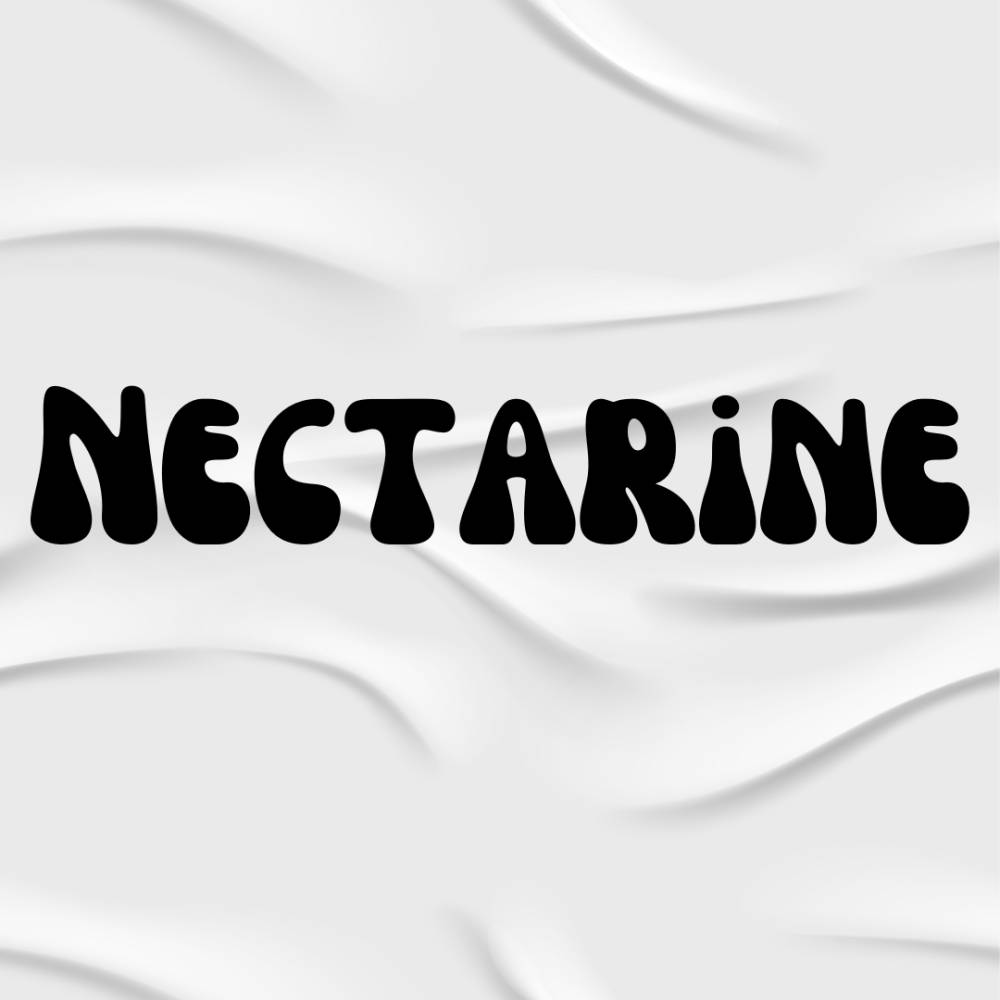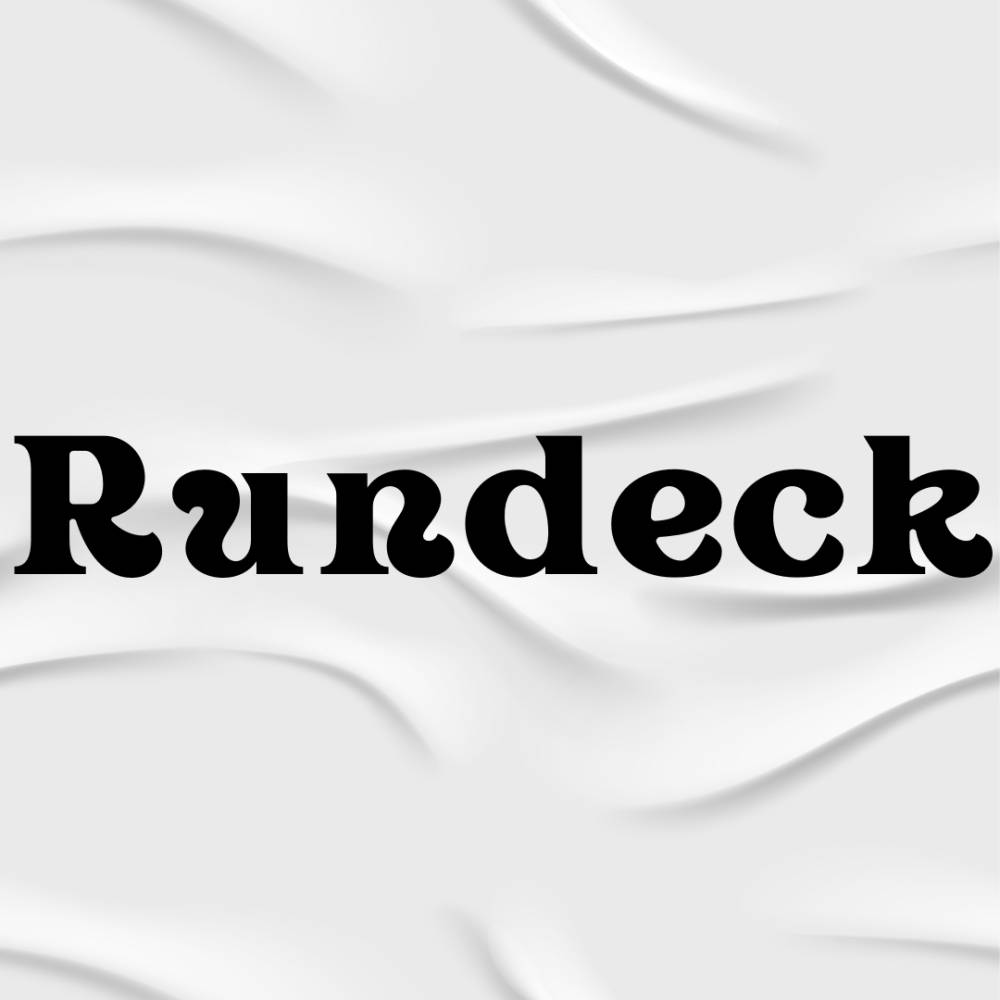
7 Rekomendasi Font Vintage Canva buat Desain Retro
Seiring dengan berkembangnya desain grafis, sentuhan retro kembali menjadi tren yang digemari. Desain-desain yang mengusung nuansa vintage mampu memberikan kesan klasik, unik, dan juga menghadirkan nostalgia. Namun, untuk benar-benar membuat desain yang memberikan pengalaman kembali ke masa lalu, adalah hal yang tricky.
Bukan hanya elemen gambar dan warna saja yang perlu diperhatikan, font menjadi elemen yang patut dipikirkan untuk menarik perhatian audiens. Untuk memudahkanmu membuat desain retro yang mampu membuat audiens bernostalgia, berikut adalah tujuh rekomendasi font vintage Canva gratis yang bisa kamu coba.
1. Bright Retro
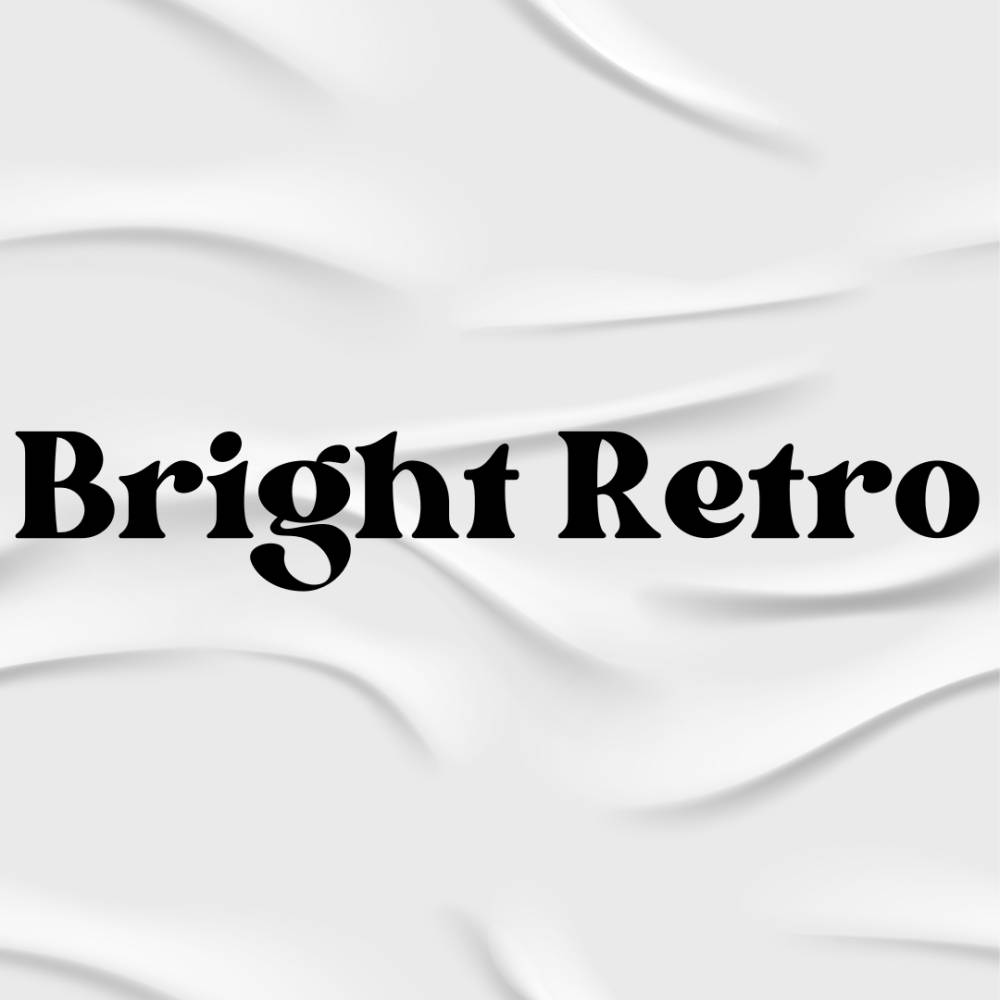
Ilustrasi font canva (dok. Canva) Font Bright Retro membawa mu kembali ke era 80-an dengan karakter tipografi yang bold dan dinamis. Dengan bentuk huruf yang mencolok, Bright Retro mampu menciptakan kesan yang ceria dan penuh semangat, sangat cocok untuk desain yang ingin menonjolkan nuansa retro yang cerah dan positif. Huruf-hurufnya yang berani memancarkan energi positif dan keberanian dalam setiap desainnya.
Kombinasi antara ketajaman sudut dan kejelasan huruf membuat Bright Retro menjadi pilihan yang menarik buat kamu yang ingin menyelami keindahan era 80-an dengan sentuhan modern. Dengan gaya tipografi yang khas, font ini tidak hanya menjadi penghias visual, tetapi juga alat untuk menggambarkan kegembiraan dan kebebasan dari zaman yang lebih simpel. Kesederhanaan dan keberanian Bright Retro membuatnya menjadi pilihan yang tak terelakkan bagi para desainer yang ingin menghadirkan suasana nostalgic dalam desain mereka.
2. Harlow
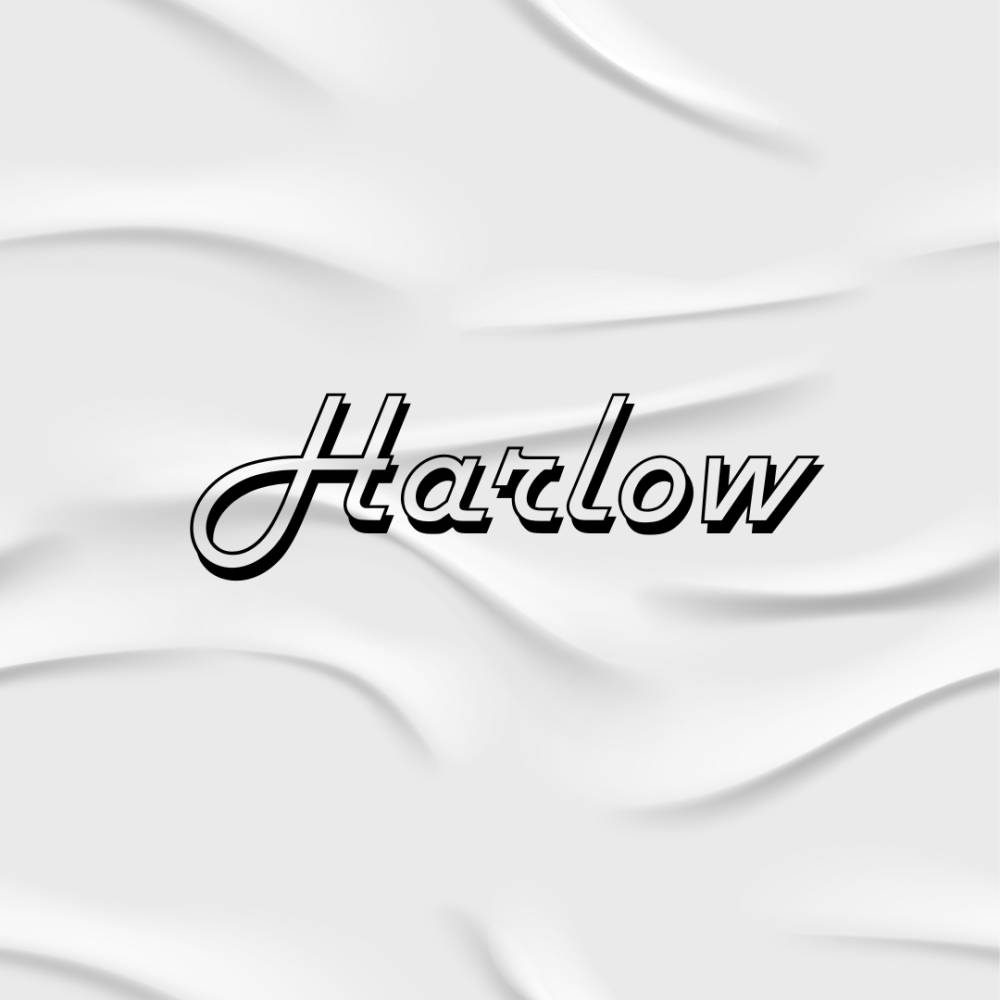
Ilustrasi font canva (dok. Canva) Font Harlow memukau dengan garis-garis elegan dan kesan klasik yang memperkaya setiap desain retro. Dengan huruf yang melengkung secara anggun, Harlow memberikan sentuhan glamour yang tak tertandingi pada setiap desainnya. Kelembutan dan keanggunan karakter hurufnya menjadikan Harlow sebagai pilihan ideal untuk desain yang mengusung gaya vintage yang lebih mewah dan anggun.
Kombinasi antara elemen-elemen artistik dan kejelasan tipografinya membuat Harlow cocok digunakan dalam berbagai konteks, dari desain poster hingga kemasan produk. Gaya yang timeless dari Harlow tidak hanya menciptakan estetika visual, tetapi juga menghadirkan keindahan yang tahan lama dalam setiap karya. Buat penggemar desain yang menghargai sentuhan klasik dan kemewahan, Harlow menjadi opsi yang tak bisa diabaikan dalam menciptakan nuansa retro yang menggoda dan berkelas.
3. Hobo
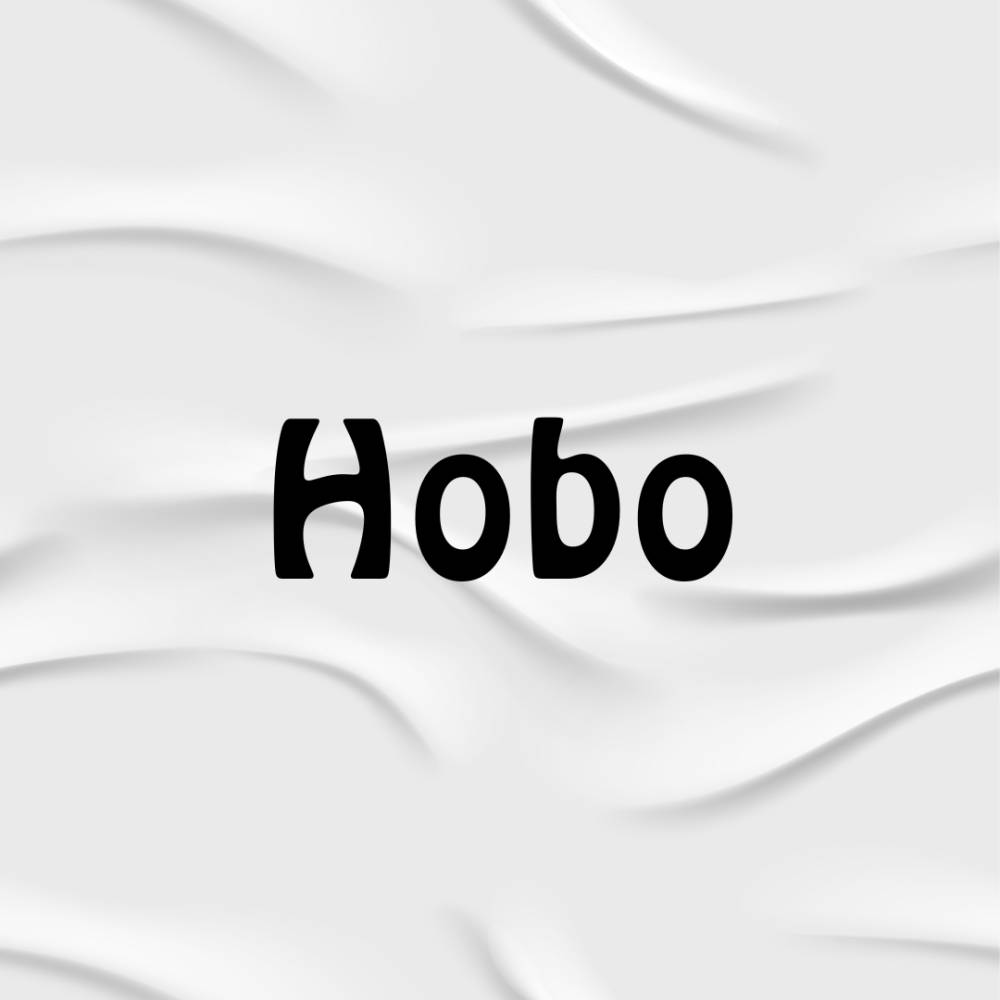
Ilustrasi font canva (dok. Canva) Font Hobo memberikan nuansa retro yang santai dan kasual dengan karakter huruf yang unik dan simpel. Desainnya yang tidak berlebihan membuatnya menjadi pilihan yang tepat untuk desain yang ingin menciptakan kesan yang ramah dan akrab. Keunikan Hobo terletak pada bentuk hurufnya yang sederhana namun memikat, menciptakan kesan yang hangat dan tidak terlalu formal.
Gaya kasualnya membuat Hobo sangat sesuai digunakan dalam berbagai konteks desain, baik itu untuk poster, logo, maupun materi promosi lainnya. Kecocokan antara desain yang santai dan kejelasan tipografi menjadikan Hobo sebagai font yang mudah diakses dan digunakan oleh berbagai kalangan desainer. Buat kamu yang menghargai nuansa ramah dan tidak terlalu resmi, Hobo jadi pilihan yang tepat untuk menambahkan sentuhan vintage pada karya-karya desainmu.
4. Sacco
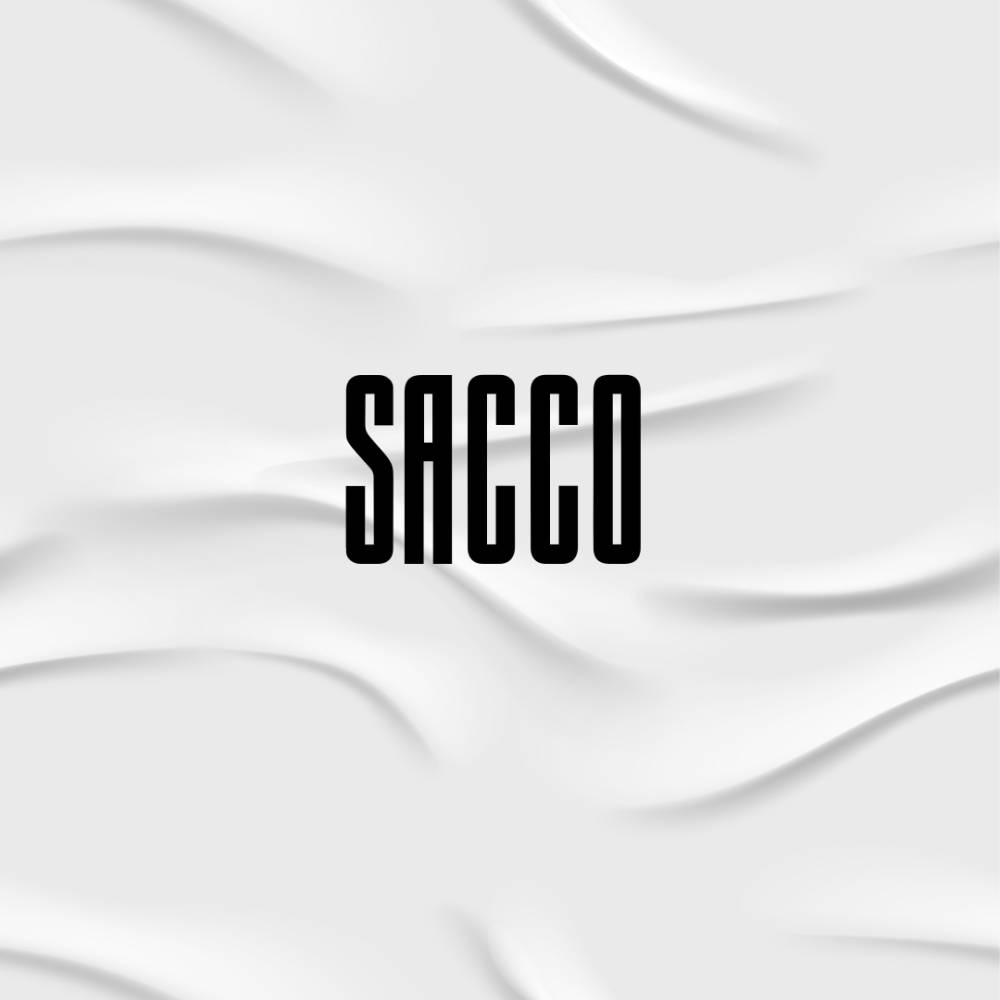
Ilustrasi font canva (dok. Canva) Font Sacco menghadirkan sentuhan unik dalam desain retro dengan perpaduan nuansa industrial dan urban yang menarik. Karakter hurufnya yang kokoh dan tegas memberikan kesan maskulin dan modern pada setiap desain. Sacco tidak hanya sekadar font, melainkan karya seni tipografi yang menciptakan atmosfer klasik yang menyatu dengan gaya kontemporer.
Keanggunan tipografi Sacco menjadi daya tarik utama, memberikan kemampuan untuk menonjol dalam berbagai desain, mulai dari poster hingga branding. Sacco tidak hanya memanifestasikan klasik dan modern, tetapi juga memberikan fleksibilitas dalam menyampaikan pesan desain. Dengan keseimbangan yang apik antara ketegasan dan keanggunan, Sacco menjadi pilihan menarik untuk desainer yang ingin menciptakan desain retro dengan sentuhan metropolitan yang kuat.
5. Margin
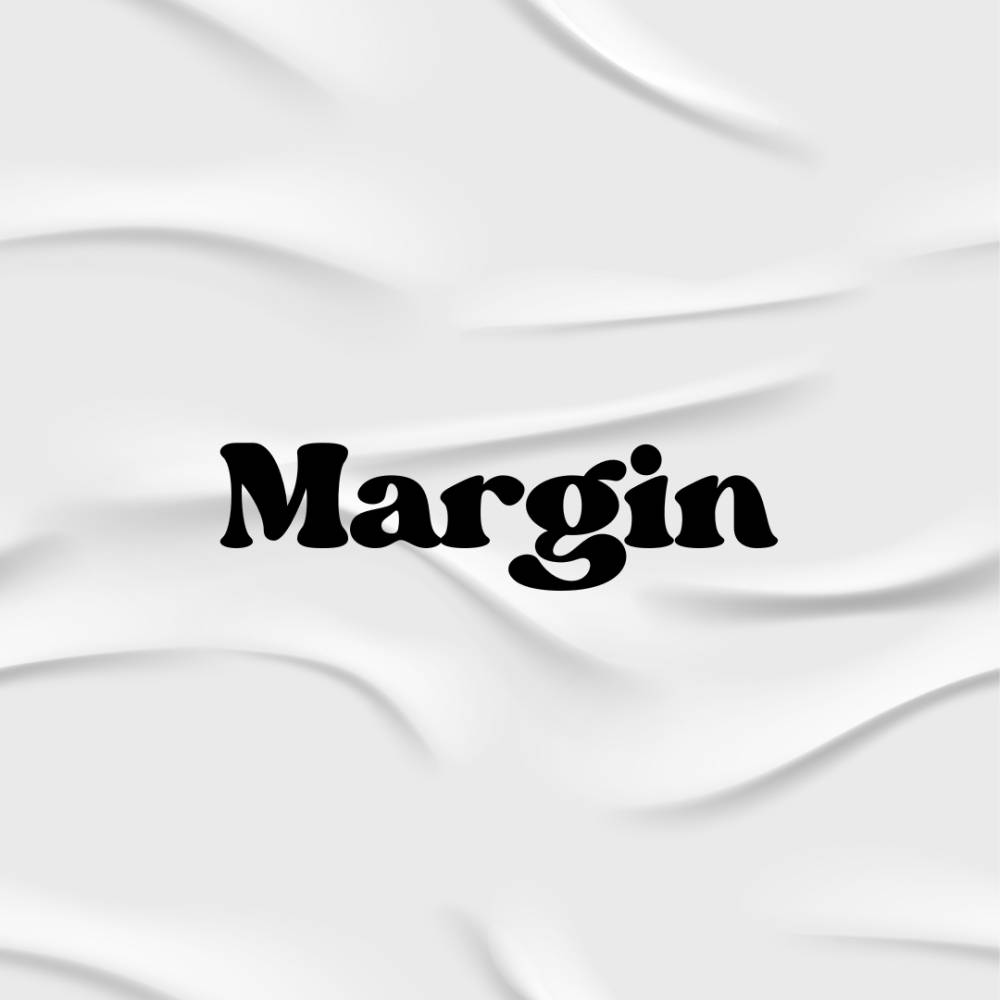
Ilustrasi font canva (dok. Canva) Font Margin memberikan kesan elegan dan sederhana, membawa nuansa retro yang timeless ke dalam desain. Dengan proporsi huruf yang seimbang, Margin memberikan sentuhan klasik yang tetap simpel namun mengesankan. Gaya tipografinya menciptakan desain yang ringan namun berkelas, memberikan fleksibilitas untuk digunakan dalam berbagai konteks.
Selain itu, kejelasan karakter huruf Margin membuatnya mudah dibaca, menjadikannya pilihan yang tepat untuk desain teks yang ingin tetap elegan. Kemampuannya untuk menyesuaikan diri dengan berbagai proyek, mulai dari desain logo hingga tata letak majalah, membuat Margin menjadi aset berharga bagi para desainer. Dengan sentuhan retro yang tidak berlebihan, Margin membuktikan bahwa keindahan sederhana dapat menjadi kunci untuk menciptakan desain yang menarik dan efektif.
Pemilihan font yang tepat dapat memberikan nilai tambah pada desain retro-mu. Pastikan untuk mempertimbangkan konteks dan nuansa yang ingin kamu sampaikan kepada audiens. Dengan menggunakan font-font vintage Canva seperti Bright Retro, Harlow, Hobo, Sacco, Margin, Nectarine, dan Rundeck, kamu dapat menciptakan desain-desain yang tidak hanya menghadirkan nuansa klasik, tetapi juga memikat dan mengesankan audiensmu. Selamat berkreasi!